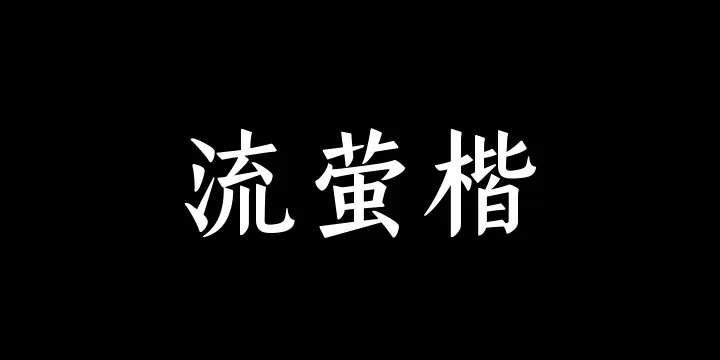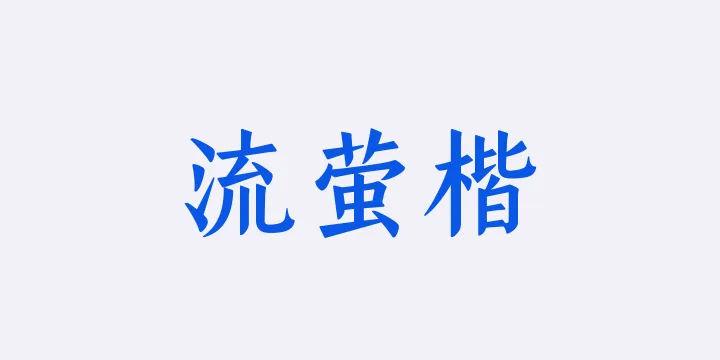
字体全名: 山海流萤楷65W
字体简介: 山海流萤楷65W,是一款全新的楷体字体,是山海流萤楷字体家族系列中的常规粗细款,编号65W,包含汉字9169个,符号200+个。该字体字形优美文雅,诗意内敛,取楷体细腻的书写笔画,书法的运笔走势蕴含其中,流畅自然,蕴含东方审美韵味,尽显优雅从容,秀雅清新。
所属分类: 楷体